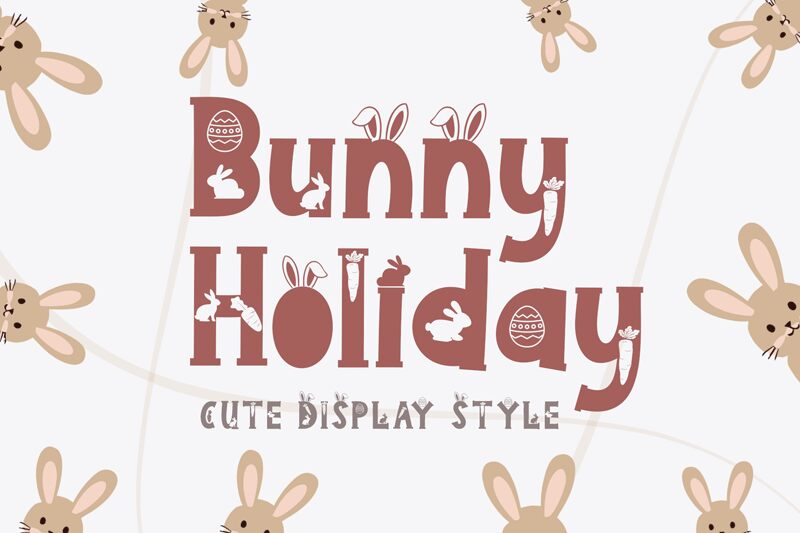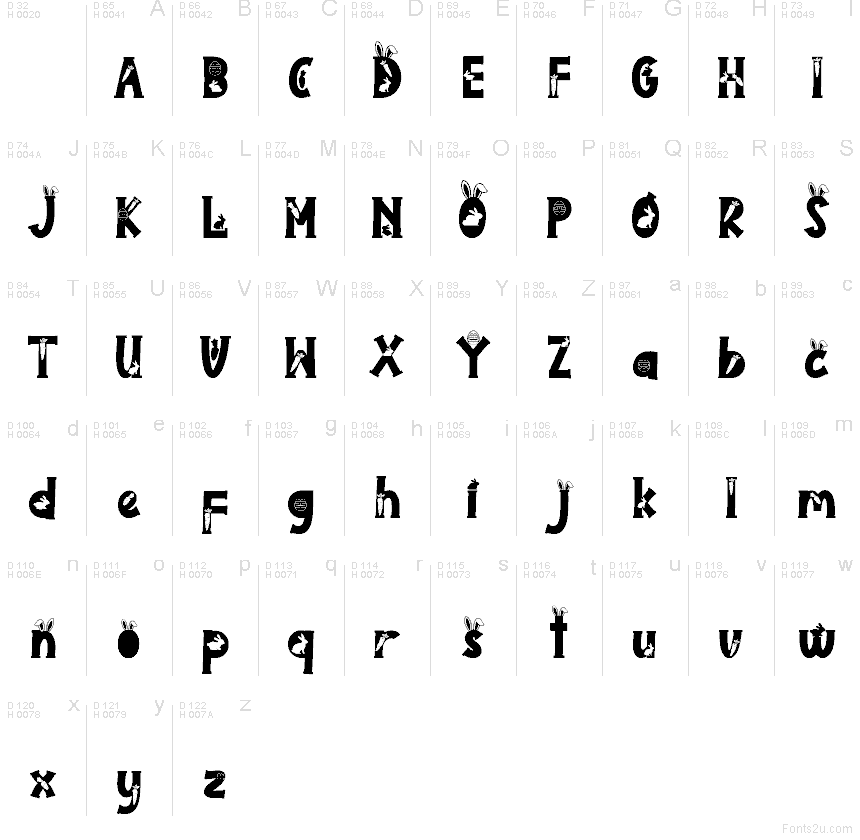
Bunny Holiday
Bunny Holiday par Yoga Letter est une police d'affichage gratuite pour Pâques, dotée de caractères arrondis rappelant le style blackletter et ornés de petits détails évoquant des lapins. Le mélange d'oreilles de lapin, de silhouettes, d'œufs de Pâques et de carottes lui confère une esthétique thématique découpée, parfaitement cohérente.
Bunny Holiday est une police gratuite idéale pour les cartes de Pâques, les flyers printaniers, les invitations de fête, les bannières de boutique, les décorations de classe et les étiquettes de vacances. Ses détails rappelant les jardins et les lapins conviennent parfaitement aux projets nécessitant une touche saisonnière sans décoration supplémentaire, surtout lorsque la typographie devient un élément central de l'illustration.